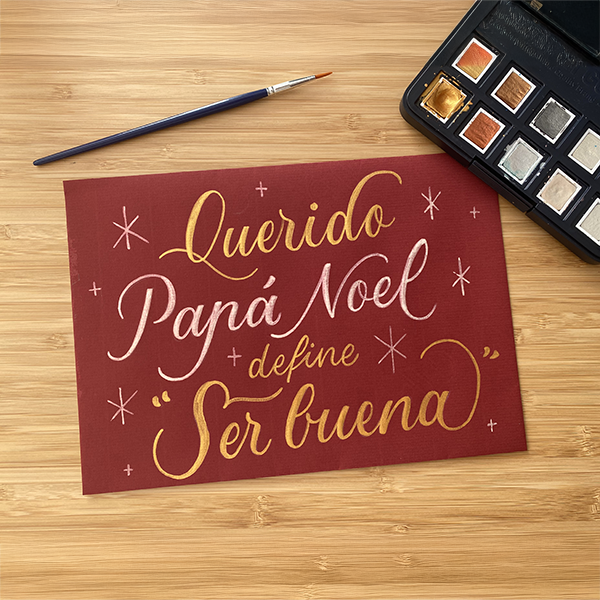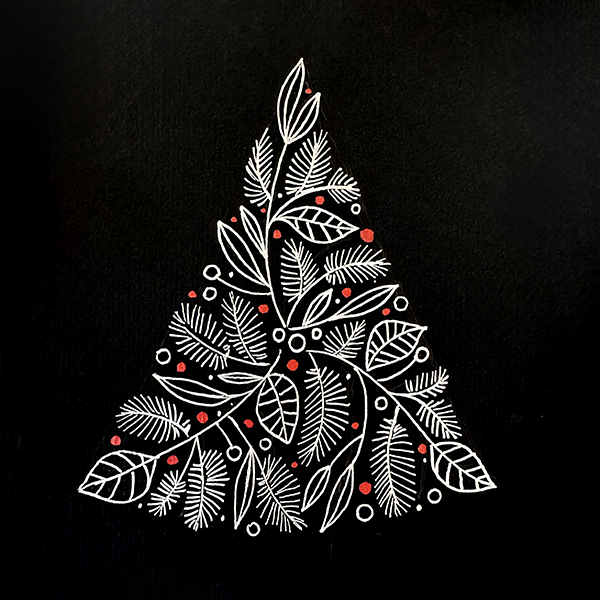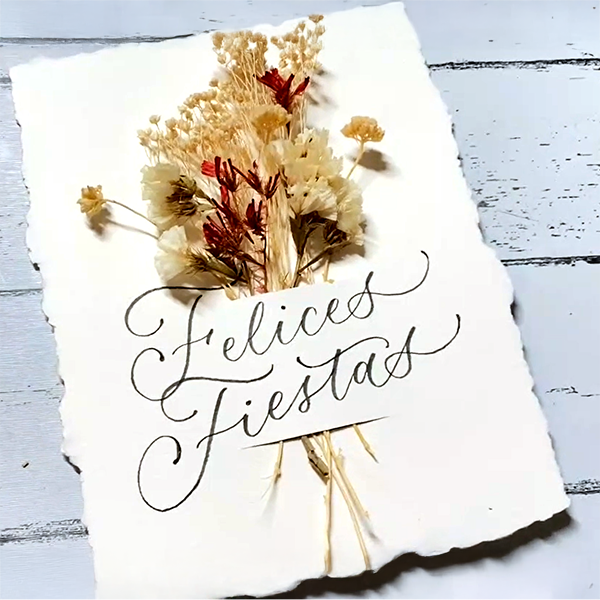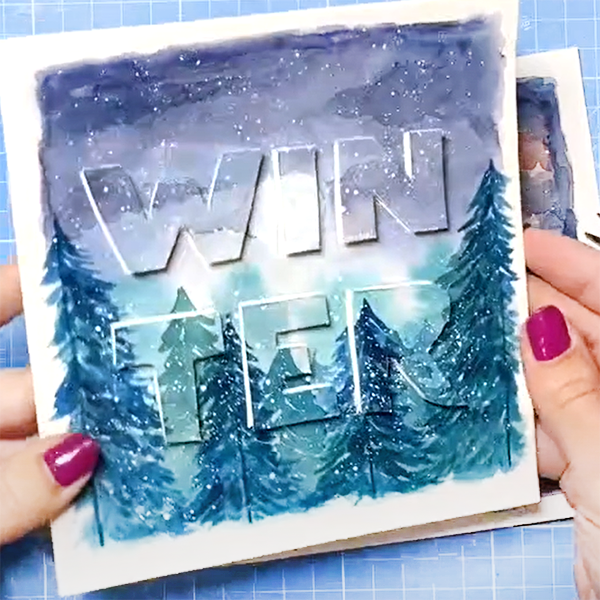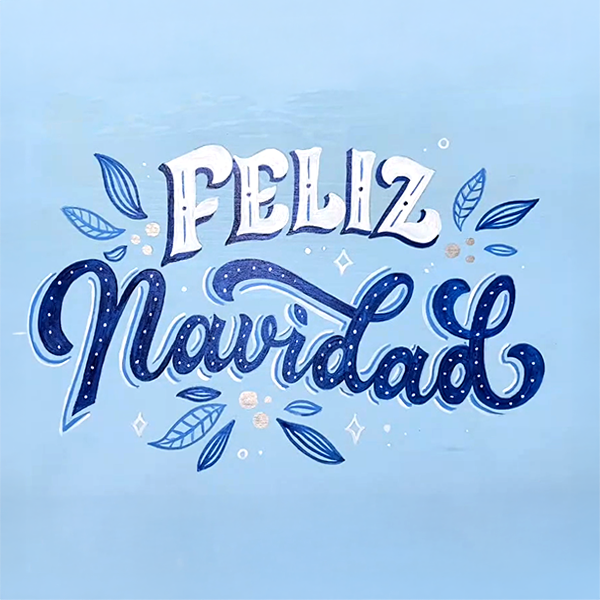
Qué encontrarás en este curso
Este curso es una recopilación de clases con temática navideña que se dieron dentro de una actividad de suscripción mensual entre 2021 y 2024. Algunas clases se dieron en directo y los vídeos no están editados: las verás tal y cómo se dieron en su momento.
Aquí tienes los proyectos que aprenderás a hacer
en estas clases:
Postales de acuarela 3D
Si quieres probar algo diferente a las típicas postales, anímate con esta versión 3D que combina un precioso paisaje de acuarela con letras en relieve. ¡Querrás enseñarla durante todo el año!
Serif lettering
Las letras con serifas bifurcadas son muy decorativas, y perfectas para utilizar en Navidad. En esta clase aprenderás a dibujar este estilo de lettering y a aplicarlo en una postal que combina rotuladores acuarelables y acuarelas metalizadas.
Tintas metalizadas
Anímate a hacer tu felicitación para estas fiestas sobre un fondo oscuro. Las acuarelas y rotuladores metalizados aportan un extra de magia a estas fiestas, y los diseños que te propongo en esta clase son a prueba de fallos. ¡Éxito asegurado!
Script lettering
Script lettering, letra manuscrita, cursiva... son diferentes maneras de llamar a este tipo de letra que enamora a todo el mundo. Sea cual sea el tipo de script que uses en este proyecto, aprenderás a dibujarlo a lápiz desde cero.
Caligrafía navideña
Crea tres postales con aire romántico mientras practicas la caligrafía monolínea y con brush pen más delicada. Descubre diferentes maneras de escribir las frases más populares de la Navidad y adáptalas a tu tarjeta perfecta.
Acrílico sobre madera
Para terminar, cambiaremos los rotuladores por pinceles y pintura acrílica, y crearemos un letrero navideño perfecto para colocar en la puerta de tu casa, encima de la chimenea o en cualquier otro sitio que se te ocurra. ¡Manos a la obra!
Por qué aprender lettering es una buena idea
El lettering es una habilidad artística que no solo despierta tu creatividad, sino que también puede convertirse en una valiosa herramienta profesional.
Tanto si lo practicas como hobby o quieres explorar nuevas oportunidades laborales, aprender lettering te abre las puertas a un sinfín de posibilidades. Puedes aplicarlo en diseño gráfico, creación de logotipos, papelería personalizada, murales, y mucho más. Además, lo genial del lettering es que no estás limitado a un solo tipo de material: puedes experimentar con rotuladores, pinceles, acuarelas, tinta, e incluso herramientas digitales.